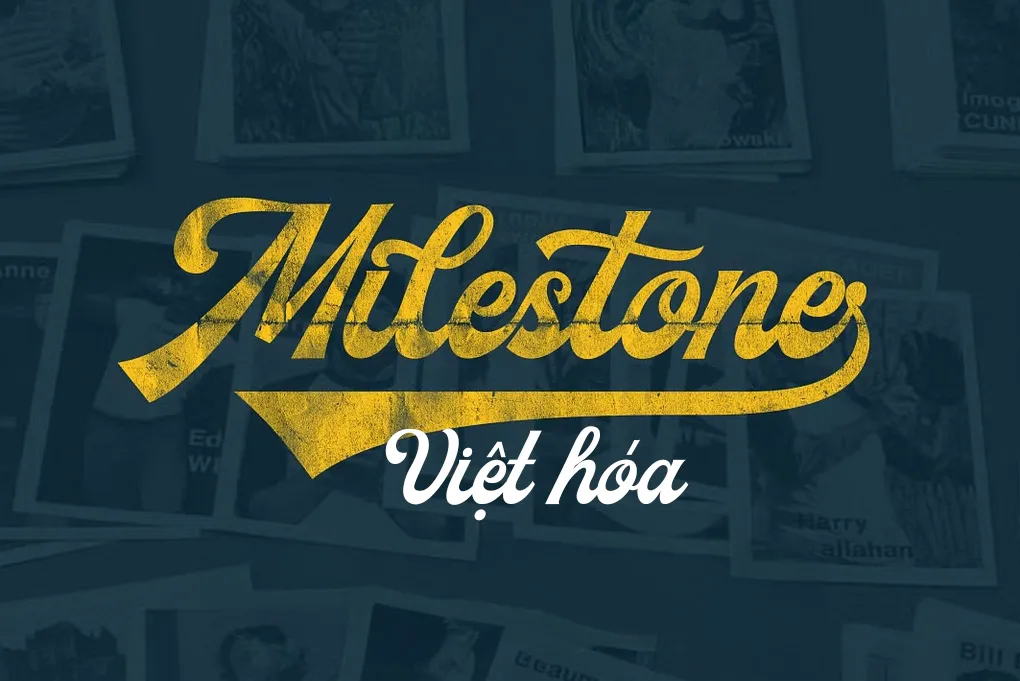
Milestone Script Việt hóa là một font chữ mang phong cách script retro – vintage, với đường nét uốn lượn, mềm mại nhưng vẫn toát lên sự mạnh mẽ và cá tính. Các nét chữ được thiết kế thủ công với độ tương phản cao, kết hợp hiệu ứng cọ vẽ bụi bặm, rất phù hợp cho các thiết kế mang màu sắc hoài cổ, cổ điển nhưng hiện đại.